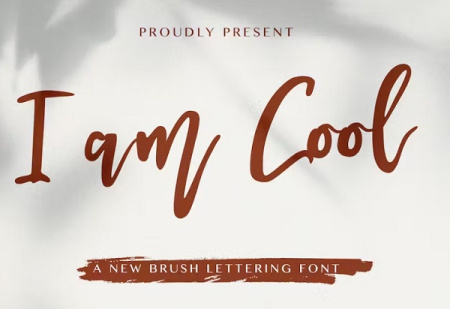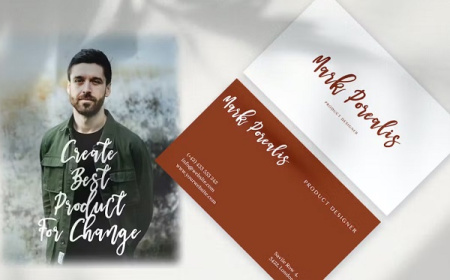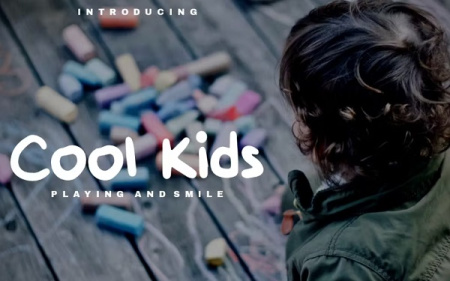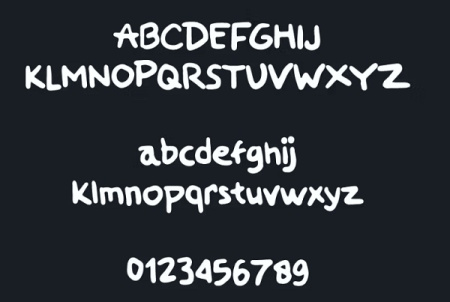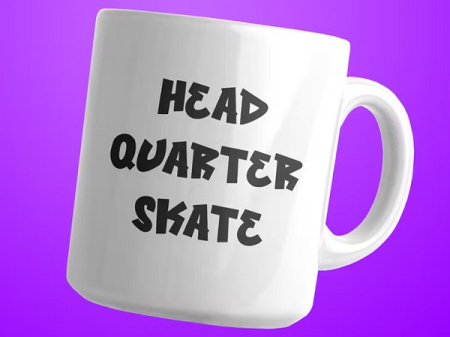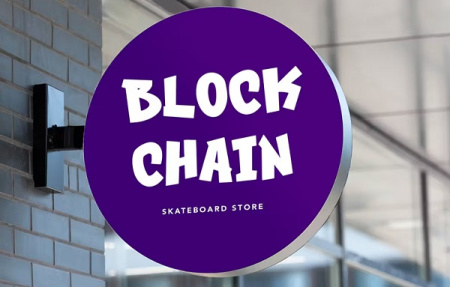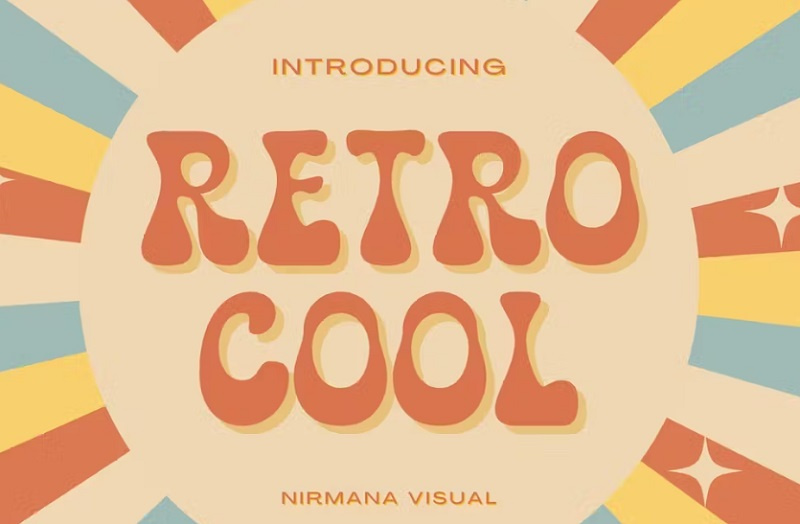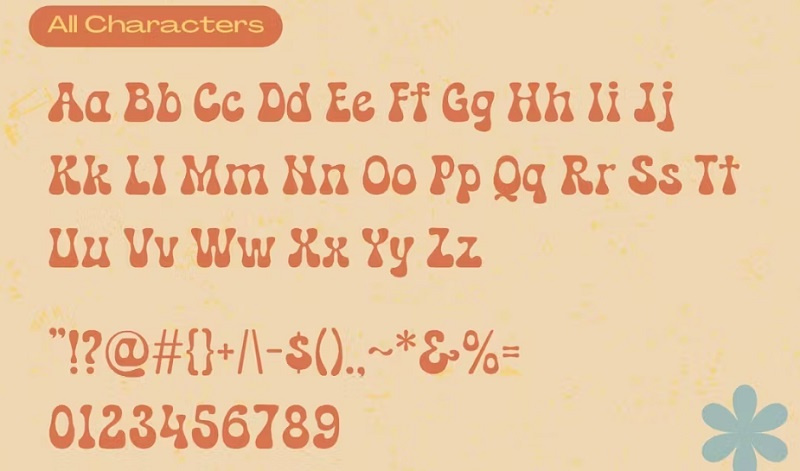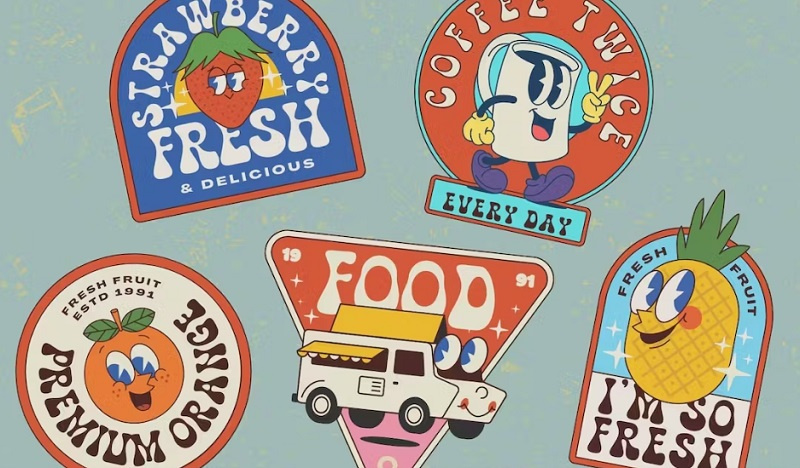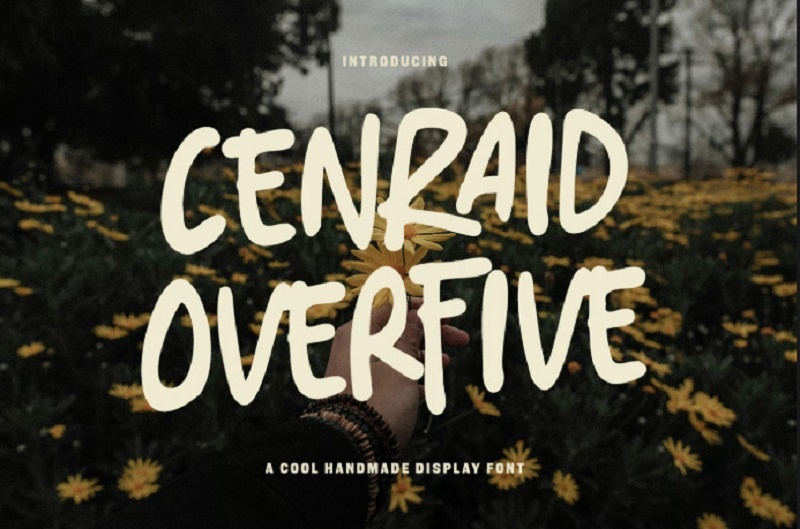
دانلود 5 فونت انگلیسی باحال I am Cool
دانلود فونت انگلیسی باحال در جی اف ایکس دانلود. این مجموعه شامل 5 فونت باحال انگلیسی می باشد. این فونت های باحال برای برندینگ ، دعوت عروسی، کارت ویزیت، برند لوگو، امضا و حتی خوشنویسی مناسب است. همچنین با کمک آنها می توانید یک لوگو یا قاب زیبا برای خانه خود بسازید. یا برای جلد کتاب، لوازم التحریر، بازاریابی، وبلاگ، مجلات و موارد دیگر استفاده کنید. در ادامه با مشاهده پیش نمایش این فونت های باحال انگلیسی با ما همراه باشید.
Retro Cool یک فونت انگلیسی باحال با طراحی به سبک قدیمی است. این فونت باحال را برای انواع پروژه های طراحی، از جمله لوگو و برندسازی، پست های رسانه های اجتماعی، تبلیغات و طرح های محصول می توانید استفاده کنید. شامل فرمت های otf - ttf و woff می باشد.
اگر به دنبال فونت های باحال انگلیسی برای متفاوت‌ تر شدن طراحی‌ های خود هستید، این مجموعه می‌ تواند گزینه‌ ای کاربردی برای طراحان باشد. در این بخش امکان دانلود فونت انگلیسی باحال برای طراحان فراهم شده و می‌ توانید فونت‌ هایی با سبک‌ های مدرن، خلاقانه، فانتزی و خاص را برای پروژه‌ های مختلف انتخاب کنید. این فونت‌ ها برای طراحی پوستر، بنر، لوگو، پست و استوری اینستاگرام، کاور، تبلیغات، بسته‌ بندی و انواع پروژه‌ های گرافیکی مناسب هستند و به شما کمک می‌ کنند ظاهر نوشته‌ ها را جذاب‌ تر و حرفه‌ ای‌تر کنید.
✅ نام فونت انگلیسی 1: I am Cool
✅ نام فونت انگلیسی 2: Cool Kids Font
✅ نام فونت انگلیسی 3: Cool Sensation
✅ نام فونت انگلیسی 4: Retro Cool
✅ نام فونت انگلیسی 5: Cenraid Overfive Cool